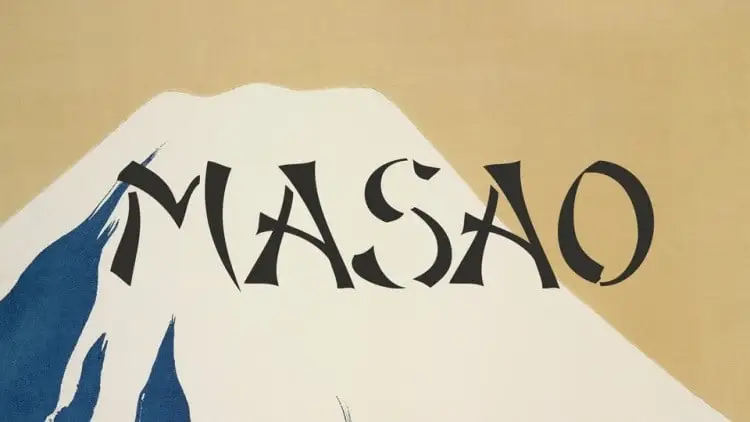
A fonte ‘Masao Display Font’, criada por Jonathan Paterson, é uma tipografia tipo-display que se inspira na cultura japonesa. Suas linhas orientais e elegantes a tornam perfeita para projetos de alto nível como posters, headlines e capas de livros. Através de seu design detalhado e minimalista, esta fonte oferece um aspecto decorativo que se destaca em qualquer aplicação visual. Seja ela usada em jornais e revistas ou em camisetas e adesivos, ‘Masao Display Font’ é uma escolha inteligente para aqueles que buscam transpor o encanto da cultura japonesa em seu trabalho de design.